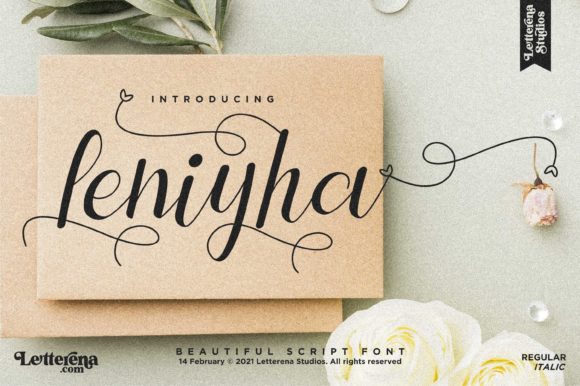
Ления - стильный и невероятно элегантный шрифт сценария.
Он выглядит потрясающе на свадебных приглашениях, благодарственных открытках, цитатах, поздравительных открытках, логотипах, визитках и любом другом дизайне, который нуждается в рукописном прикосновении.